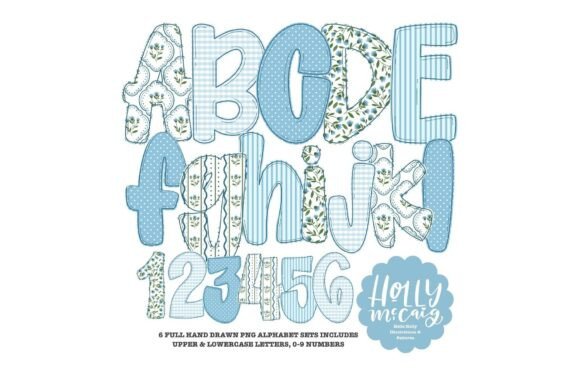
Cottage Chic Doodle Alphabet - Blue Font
قد يكون العثور على عناصر التصميم المناسبة أمرًا صعبًا، ولكن Cottage Chic Doodle Alphabet - Blue Font يقدم مجموعة استثنائية ترتقي بعملك على الفور.
سواء كنت تقوم بإنشاء منتجات الطباعة عند الطلب أو دعوات الزفاف أو رسومات وسائل التواصل الاجتماعي، فإن Cottage Chic Doodle Alphabet - Blue Font هو الخيار المثالي.